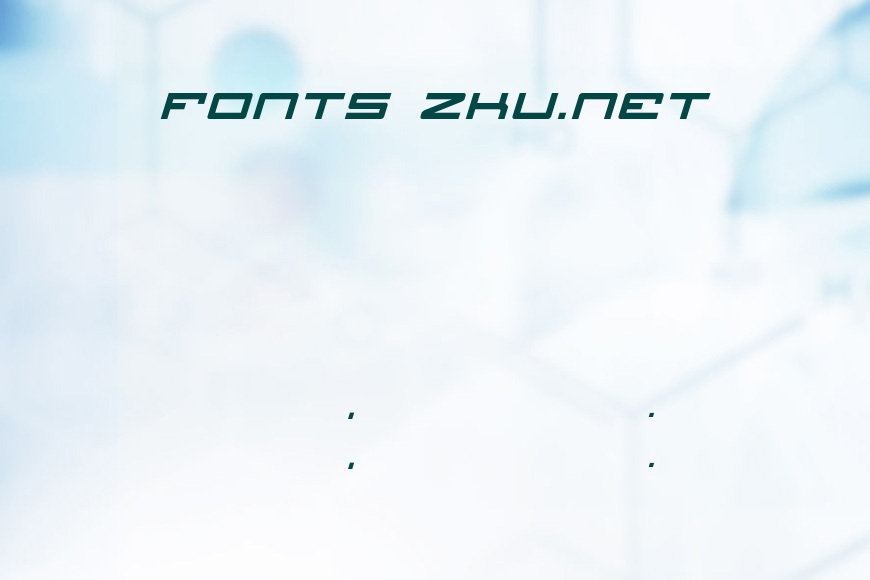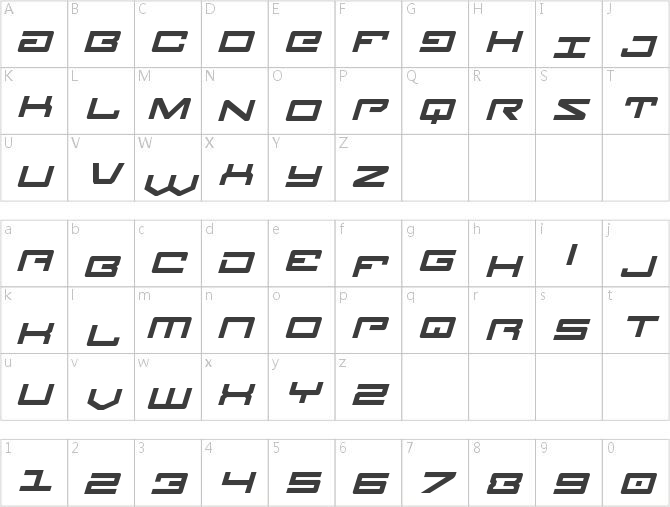
legionboldital
字体名称 Legion Bold Italic
设计师 Daniel Zadorozny
legionboldital字体字库是一款让人赏心悦目、百看不厌的英文字体,适合各类广告和产品包装设计应用,字体大小0.02MB,格式为ttf字体,上传用户是芜耆芜,作者/版权方为未知。